上海,2025 年 7 月 12 日 —— 近日,由全球知名字体公司 Monotype(蒙纳字库) 与 Frustum Design Gallery(本见)联合发起的“Helvetica Now, Everywhere”公共艺术项目在上海亮相。
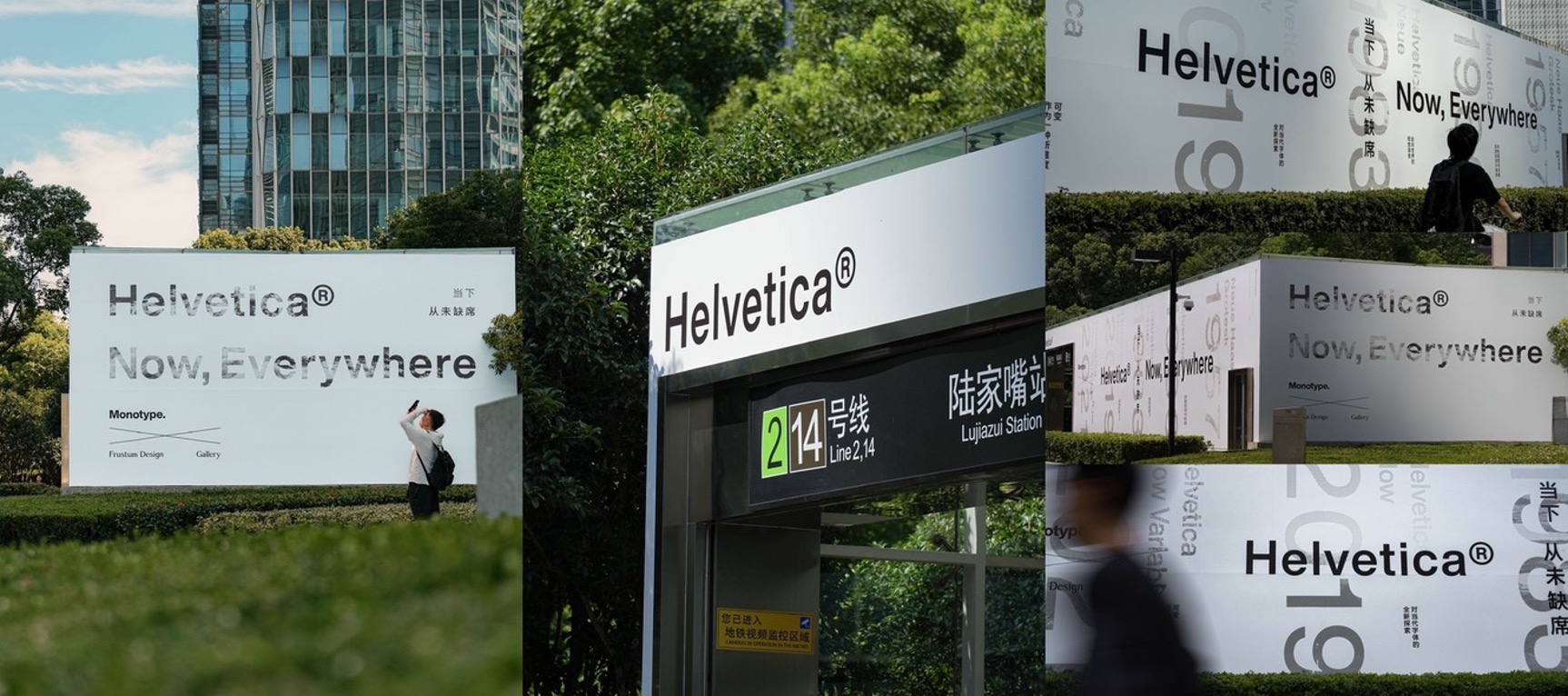
作为20世纪最具影响力的字体之一,Helvetica 以陆家嘴地铁站和前滩太古里为展场,首次以主角身份“出街”,通过巨型展板与动态海报与公共空间对话,引发各界对“日常设计”的广泛讨论。
从瑞士经典到城市肌理:Helvetica“从未缺席”
此次项目以“当下,从未缺席”为核心主题,将 Helvetica 这一诞生于瑞士经典字体推向公众视野。1957 年,Helvetica 在战后欧洲的混沌中以“去装饰化”的利落设计确立了视觉秩序,其“中性”特质并非冷漠,而是如白纸般承载多元语境,成为纽约地铁导视、联合国会场、苹果系统等全球公共空间的“隐形秩序”。
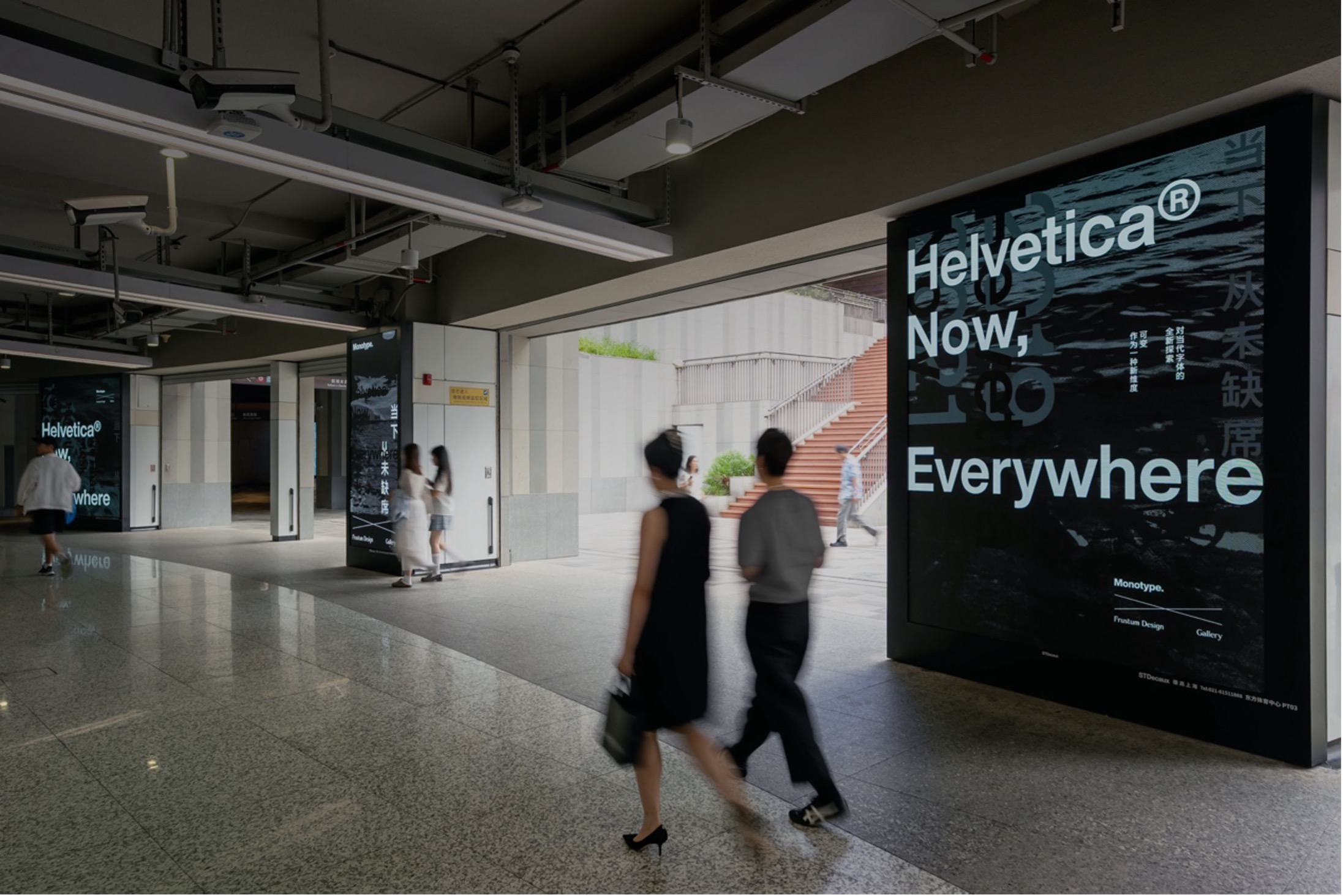
正如平面设计大师 Lars Müller 所言:“Helvetica 是城市的‘香气’,平日不显,一旦缺席便令人怅然。”
此次登陆上海,Helvetica 不仅通过巨型广告牌和空间装置放大其字形细节,更与每日数十万人次的行人形成视觉对话,让大众重新审视这一藏在城市肌理中的设计元素。
新旧碰撞与时代演进:从 Helvetica 到 Helvetica Now
展览中一个趣味场景引发热议:陆家嘴地铁站8号出入口,Helvetica 与 Arial 两款字体“意外同框”。
作为设计逻辑的两种表达,Helvetica(1957年)与 Arial(1982年)虽渊源深厚,却各有使命。前者以“精准秩序”成为设计经典,后者因适配早期激光打印与 Windows 系统普及为“实用派代表”。
如今,两者均衍生出庞大家族:Helvetica Now 系列针对数字屏幕、微小字号等场景优化,推出 Micro、Text、Display 三款视觉字号;Arial 也以 Rounded 等风格拓展应用边界。
这种同框恰恰印证了设计的多元价值。经典与实用并非对立,而是不同语境下的表达。
公众参与:关于“日常设计”的全民探索
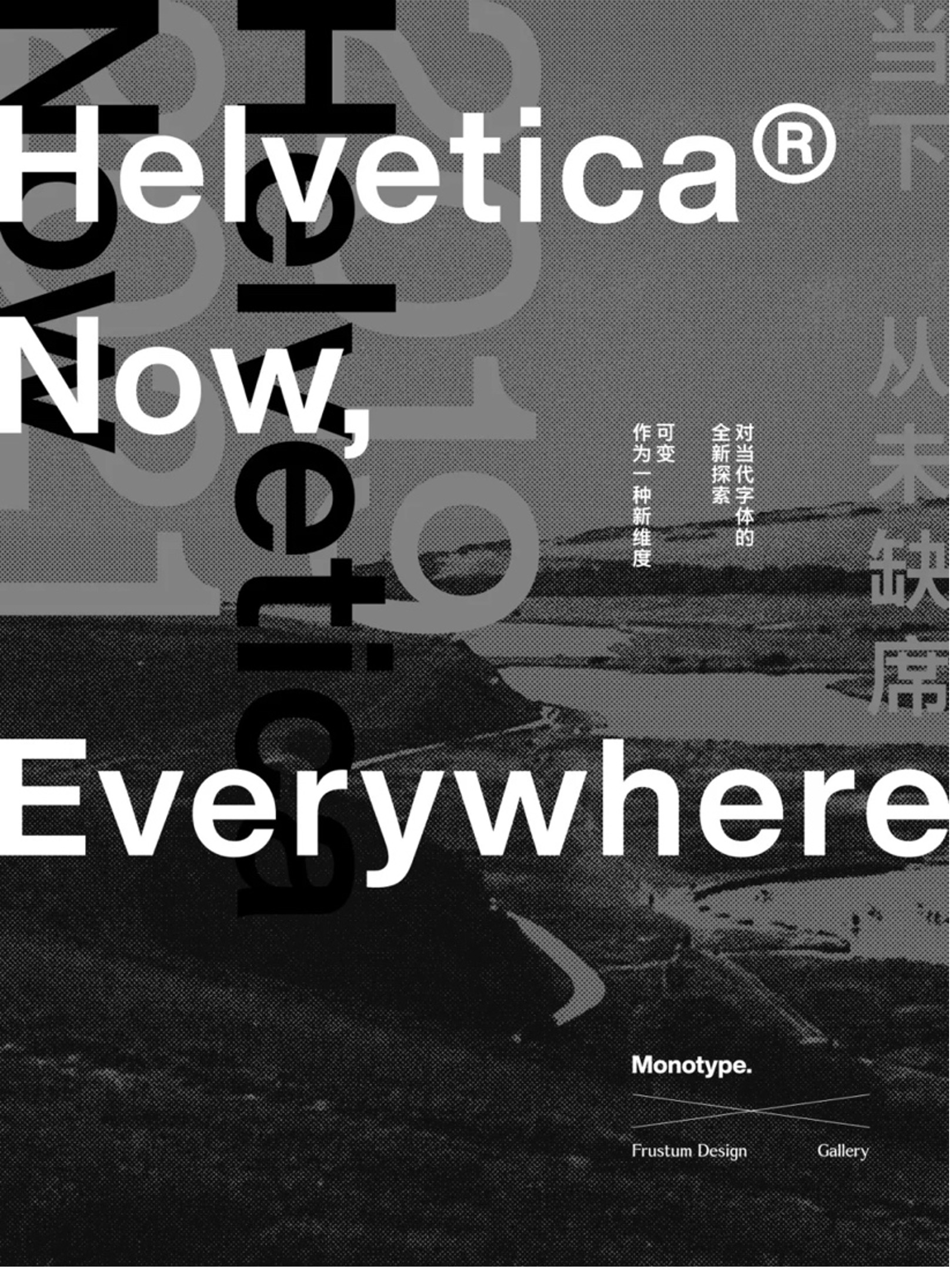
除静态展示外,项目同步发起“当下·在场——Helvetica 与我”互动计划,邀请设计师与公众分享“三个一”:一张 Helvetica 在生活中的现场图像、一句对其的直观感受、一段与之相关的场景记忆。Frustum Design Gallery 策展人 Emma Wang 指出:“Helvetica,对设计师,它可能是创作的基础;对品牌,它是视觉的语气;对路人而言,它或许习惯的存在。于是,我们希望把这场探索,交还给每个人。”
正如展览标语“当下,从未缺席”所喻:真正的经典从不困于历史,而是始终与生活共振,在时代更迭中持续书写新的设计叙事。